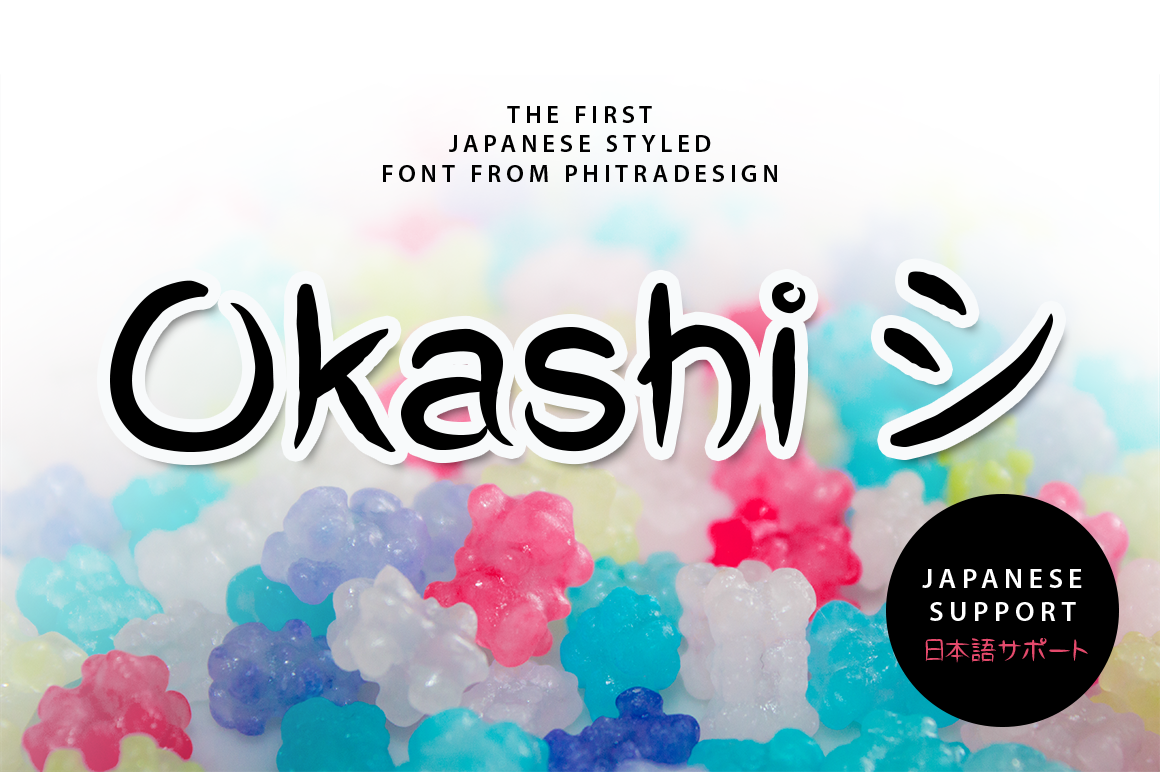
Okashi Font – Download Grátis
A fonte Okashi é uma ótima escolha para aqueles que procuram um efeito vintage e artesanal em seus projetos digitais. Desenvolvida pelo designer Philip Traamann, essa família de fontes Brush é perfeita para criar designs elegantes com toques de graça. Seu design ágil e irregular se destaca quando usada para títulos ou pequenos detalhes em texturas criativas. Okashi não apenas atende às necessidades do designer gráfico que busca uma fonte única, mas também cativa os consumidores através da personalidade única dela. A sua natureza descompromissada e acolhedora faz com que seja um elefante no circo de designs digitais atuais, oferecendo aos criativos uma maneira diferente de expressar suas ideias visuais.